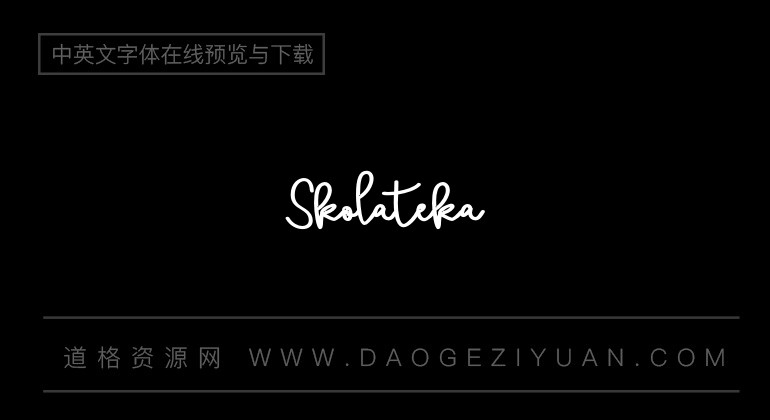
Skolateka
Skolateka 是一款由葡萄牙设计师 Joana Correia 创作的字体。它具有简洁、现代、活泼的设计风格,适用于各种印刷和网络媒体。Skolateka 的字体家族有三种:Regular、Italic 和 Bold,每种字体均有大小写字母、数字、标点符号和特殊字符。Skolateka 字体具有良好的可读性,可以用于标题、广告、海报、网站等,为你的设计提供时尚、现代的外观。
Skolateka是一款非常不错的手写艺术字体,具有很好的视觉感,适合于文化类的宣传设计、商业类品牌的广告和产品包装设计以及个性化文字排版等较多场景。